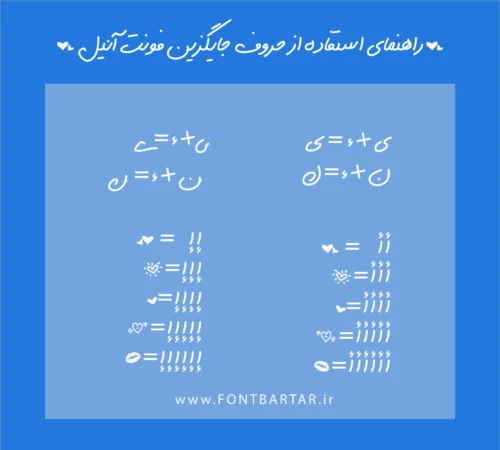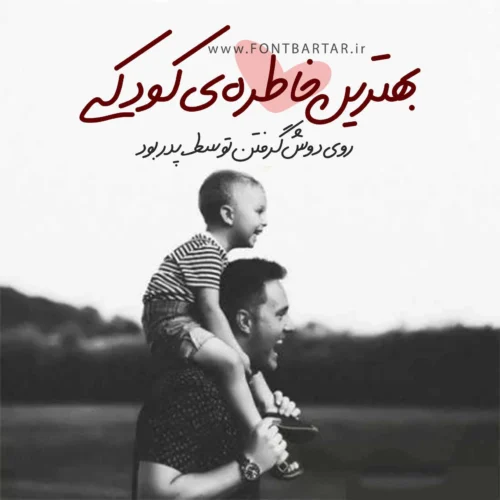
دانلود فونت فارسی آنیل
فونت دستنویس آنیل
دانلود فونت دست‌نویس آنیل | فونت فارسی خاص با حروف جایگزین
فونت دست نویس آنیل یکی از فونت‌های خاص و احساسی فارسی است که با الهام از نوشتار طبیعی دست طراحی شده و حس صمیمیت، ظرافت و خلاقیت را به طراحی منتقل می‌کند. فونت دست نویس فارسی رایگان برای طراحانی که به‌دنبال ایجاد ارتباط احساسی با مخاطب هستند، انتخابی بسیار حرفه‌ای محسوب می‌شود. وجود حروف جایگزین (Alternate Characters) در فونت آنیل باعث می‌شود نوشته‌ها طبیعی‌تر، متنوع‌تر و زنده‌تر دیده شوند و از یکنواختی فاصله بگیرند.
چرا فونت بهترین فونت دست نویس آنیل انتخابی مناسب برای طراحان است؟
فونت‌ های دست‌ نویس نقش مهمی در انتقال احساس و شخصیت برند دارند. فونت آنیل با طراحی نرم، انحنای متعادل و ضخامت کنترل‌شده، بدون افت خوانایی، جلوه‌ای متفاوت به تایپوگرافی فارسی می‌دهد.
مزایای اصلی فونت فارسی آنیل:
• طراحی دست‌نویس طبیعی و حرفه‌ای
• دارای حروف جایگزین برای تنوع نوشتاری
• خوانایی بالا در اندازه‌های مختلف
• مناسب طراحی دیجیتال و چاپ
• هماهنگ با سبک مدرن و مینیمال
کاربردهای فونت فونت فارسی آنیل
این فونت فارسی خاص برای پروژه‌های متنوعی قابل استفاده است، از جمله:
• طراحی پوستر و بنر تبلیغاتی
• کاور پست و استوری اینستاگرام
• تایپوگرافی هنری و خلاقانه
• طراحی لوگوتایپ فارسی
• طراحی بسته‌بندی محصولات
• کارت دعوت، پوستر رویداد و جشن‌ها
• محتوای احساسی و برندینگ شخصی
فونت فارسی رایگان آنیل مناسب چه کسانی است؟
• طراحان گرافیک
• تولیدکنندگان محتوا
• ادمین‌های شبکه‌های اجتماعی
• طراحان پوستر و تایپوگرافی
• برندهای شخصی و هنری
• کسب‌وکارهای خلاق
1. فونت آنیل دست‌نویس است یا فانتزی؟
فونت آنیل یک فونت دست‌نویس فارسی است که بر پایه نوشتار طبیعی طراحی شده است.
2. آیا فونت آنیل حروف جایگزین دارد؟
بله، این فونت دارای حروف جایگزین است که تنوع بصری متن را افزایش می‌دهد.